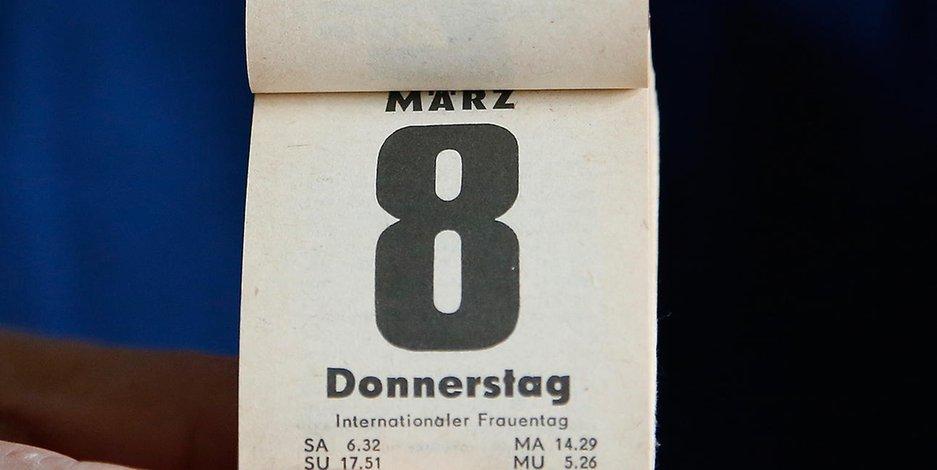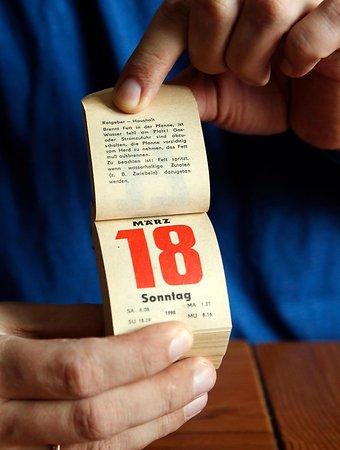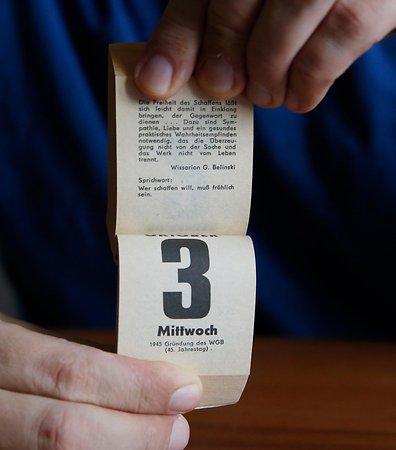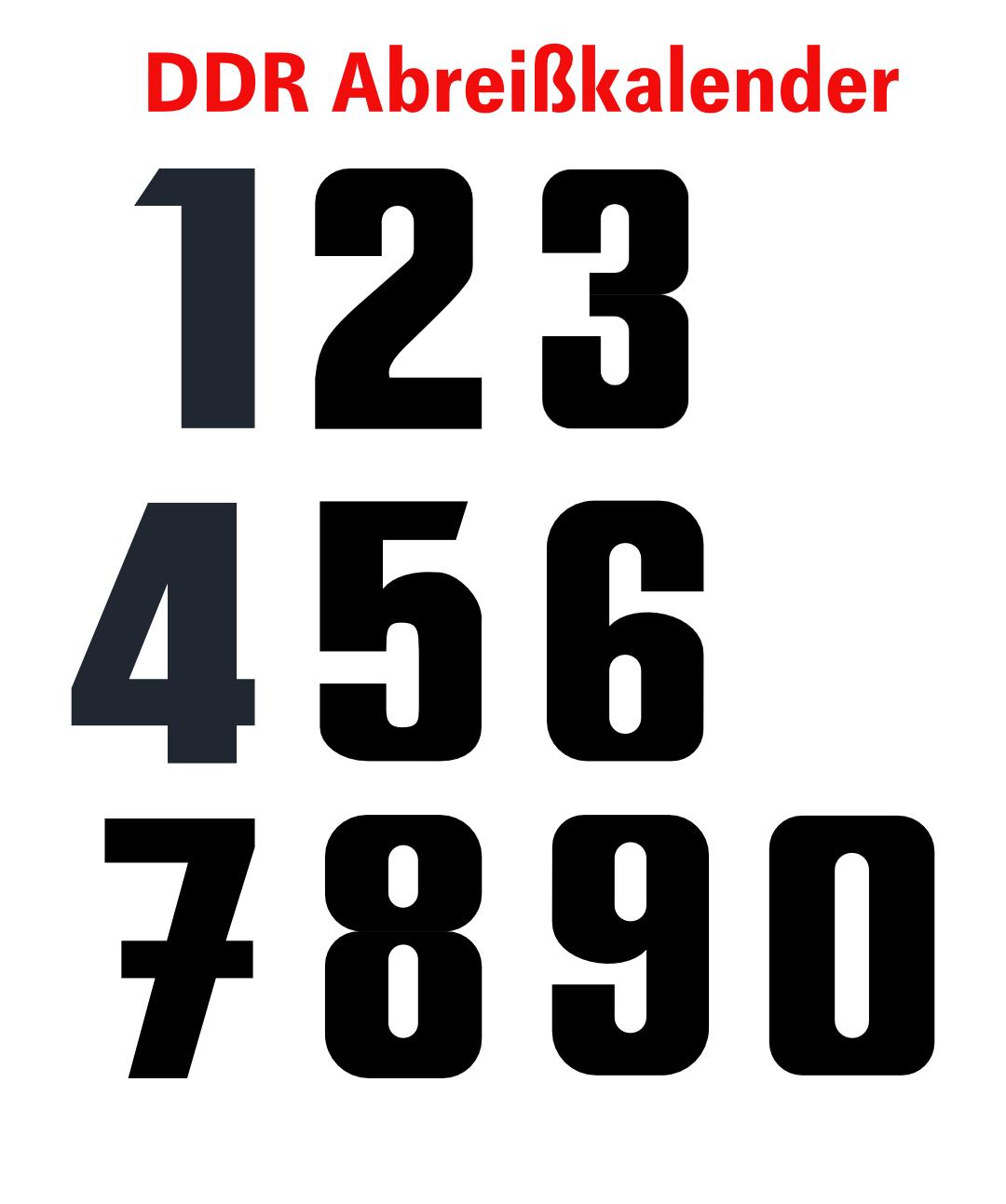
DDR-Abreißkalender / Schriftart gesucht
Die Plak von Renner erschienen bei D. Stempel hat eine ähnliche 1, die 3 und 8 passen jedoch nicht – scheint mir sehr konstruiert und erinnert an die Futura Display. Eventuell wurde diese ja für die Kalender angepasst?
Die Ziffer 1 ist schon sehr speziell. Da der Kalender über Jahre hinweg gleich aussah, liegt die Vermutung nahe, dass sie extra dafür angefertigt wurde.
die 1 gibts wie gesagt bei der Plak und ähnlich ist auch die der Futura Display, ich denke aber auch das diese eher als Vorlage dienten.
Ich habe mal, natürlich rein visuell und ohne Schriftprogramm (Affinity Designer) die Zahlen nachempfunden. Vielleicht hat jemand eine bessere Vorlage und kann daraus eine Schrift machen...